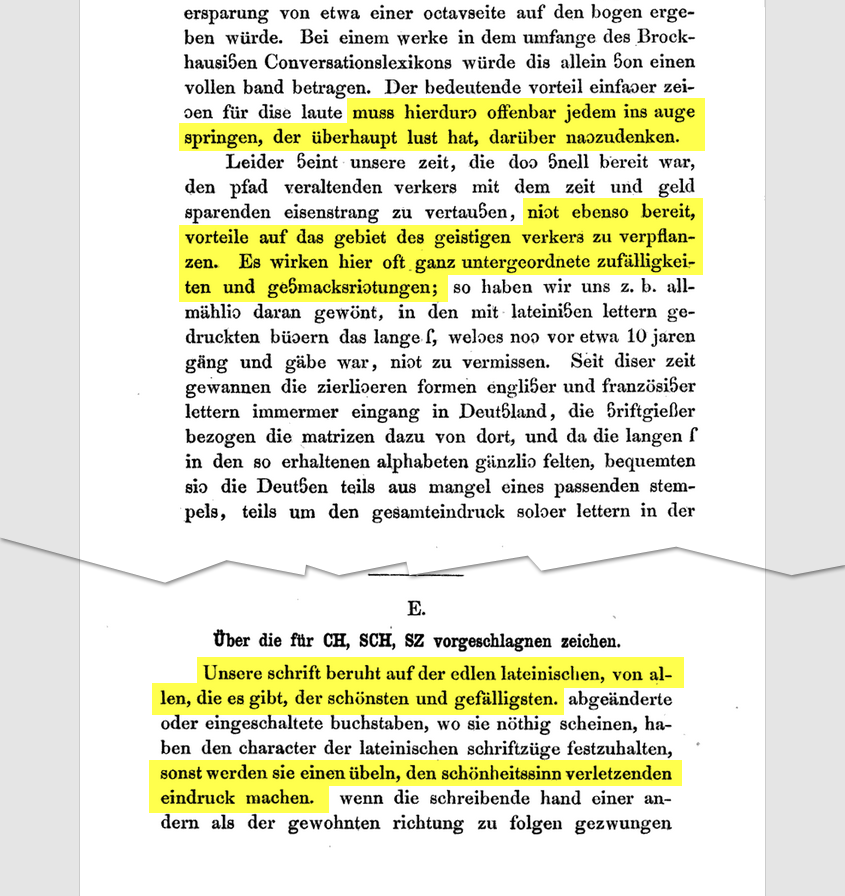
ch/sch als einzelne Buchstaben
Interessant. Wobei mir jetzt nicht so klar ist, was an diesen Formen so besonders terrible sein sollte. Einfach zu schreiben wären sie schon mal. Einigermaßen intuitiv (gespiegeltes c für ch; mit ſ kombiniert für ſch) auch.
Ist mir auɔ so gegangen, dass iɔ sogar noɔ weniger Ƨchwierigkeitn hatte, diesen Text zu lesen. das Sch / sch hat hier aber einen empfindliɔen Naɔteil, hier wird die gleiɔe Glyphe sowohl für die gemeinen, wie die Versalien verwendet, Vielleiɔt wäre hier ein Ƨ / ƨ eine bessere Wahl?
Sicherheitshalber sollte ich hier wiederholen, was ich als nächstes Tweet geschrieben habe. Hier auf Deutsch (mehr oder weniger):
Diese beiden Formen waren wahrscheinlich nicht von Theinhardt selber ausgedacht, aber ich glaube schon, dass er ihre Einführung unterstützte. Außerdem hat er wahrscheinlich die beiden Stempeln geschnitten, die für den Guss der Typen im Satz dieses kleinen Buches notwendig waren. Auch ist das Buch nicht wirklich von Grimm allein, aber sein Name ist die größere auf der Titelseite, weil er sicherlich damals schon berühmter war.
Und … die Formen sind schon grauenvoll! Auch die Idee, neue Buchstaben ins Alphabet hierfür überhaupt einzufügen. Zum Glück wurden sie nicht aufgenommen. Die Buchstabenformen waren schon relativ leicht zu lernen. Auch ich könnte nach einigen Zeilen den Text problemlos lesen. Aber nur weil solche Änderung prinzipiell machbar sind, heiß es nicht, dass ich unbedingt dafür stimmen würde 😉 Aber das ist halt nur meine persönlich Meinung dazu.
Die beiden Buchstabenvorschläge erinnern mich ein bisschen an den neuen Buchstaben des Kaisers Claudius (https://de.wikipedia.org/wiki/Claudius#Gelehrtentätigkeit).
Bei solchen Aussagen, in die Richtung "Wer das nicht (ein-)sieht ist doof!", habe ich gar keine Lust, weiterzulesen (und darüber nachzudenken).
Natürlich ist es eine Frage der Gewohnheit. Man kann darüber streiten, ob die Formen von Theinhardt geeignet wären, die Laute darzustellen bzw. abzukürzen. :-?
Inwiefern? Magst du das irgendwie begründen?
OK, dass du keine neuen Buchstaben möchtest, habe ich verstanden. Aber du schreibst selbst »auch«? Was stört dich denn noch?
Muss ich das begründen?! Offensichtlich kam der Vorschlag nicht wirklich an. Sonst würden wir sie heute im Satz haben 😂
Hat jemand von Euch Kenntnisse zu Diskussionen, das lateinische Alphabet um spezielle Zeichen für Laute zu erweitern? Also nicht um handschriftliche Variationen, die es ins Druckbild geschafft haben wie die deutschen Umlaute, sondern wirklich neue Zeichen.
Im Text werden die Vorschläge dem Autor, G. Michaelis, zugeschrieben, s. S. 37. Theinhardt tritt in der Publikation mit einem Gutachten in Erscheinung, Anhang B, Gutachten über die Zeichen für ch und sch.
Als Schriftgiessereibesitzer gab es für Theinhardt offenbar praktische Gründe, sich mit der Einführung neuer Buchtaben zu befassen, aus seinem Gutachten: »Nach der gewöhnlichen Schreibart sind zur Herstellung des Lautes von ch zwei, zur Herstellung des Lautes von sch drei Buchstaben erforderlich; sobald an deren Stelle einfache, selbständige Zeichen träten, würden nach der Berechnung der Typenzahl zur Herstellung eines gedruckten Werkes 5 bis 6 % an Typen weniger zu setzen sein, wodurch sich, namentlich mit Rücksicht auf die Breite der Typen, eine Einsparung von etwa einer Octavseite auf den Bogen ergeben würde. Bei einem Werke in dem Umfange des Brockhausischen Conversationslexikons würde dies allein schon einen vollen Band betragen.« Ist doch gut nachvollziehbar und ähnelt auch aktuelleren Design-Argumentationen, z.B. Weidemann und das DB-Logo.
Ähm ja... ẞ
Aber dann natürlich all die Erweiterungen der Unicode-Blöcke Lateinisch erweitert A bis E
Nein, denn das gemeine ß ist ja, warum und wie auch immer, aus der Handschrift in das Druckbild gerutscht und es ist nur logisch, einem Kleinbuchstaben auch einen Großbuchstaben beizugeben.
Es geht mir auch nicht um all die diakritischen Zeichen, die sich im Laufe der Jahrhunderte entwickelt haben, sondern eine bewusste Entscheidung, einen bisherigen Di- oder Polygraphen durch ein einzelnen Symbol zu ersetzen. Ich kenne das nur von Währungssymbolen.
urch Di- oder Polygraphen hätte darstellen können, wie es mit unserem Sch-Laut geschehen ist, warum auch immer...